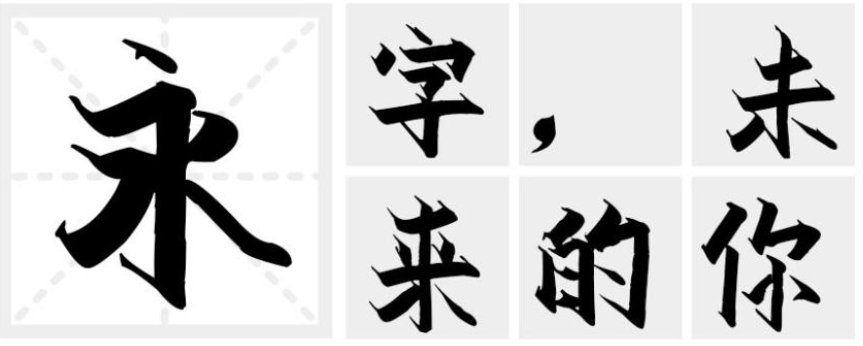
汉标雄安菲墨体|用软笔来书写的手写字体
汉标雄安菲墨体是用软笔来书写的软笔字,字型既有楷体的挺拔,又有硬笔独特的骨气,是作者所书写的众多字体中,很喜欢的一款实用的字体。
汉标雄安菲墨体
该字体是一款不错的手写字体,该字体让人第一眼看上去就有很强的视觉感,有一种朦胧感,特别是字形的框架非常完美,整体既视感非常的强,所以特别适合广告创意创作使用。
汉标雄安菲墨体